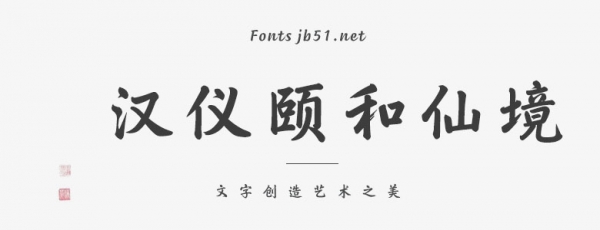
漢儀頤和仙境是由漢儀字庫出品,字體筆觸適中,字形端正,擁有簡(jiǎn)體、繁體和W三種字型,具有很好的視覺感,適合應(yīng)用于藝術(shù)設(shè)計(jì)、平面宣傳設(shè)計(jì)、網(wǎng)頁設(shè)計(jì),書法字帖等領(lǐng)域,需要的朋友可以前來本站下載。